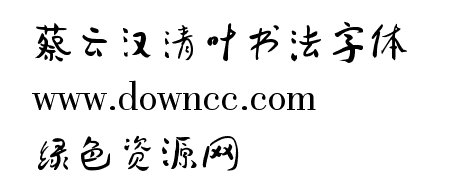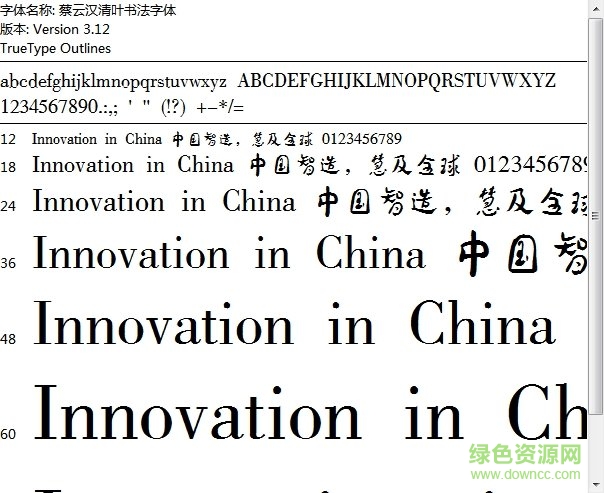
蔡云漢清葉書法字體是一款與蔡云漢清悠書法字體比較相似的蔡云漢字體,英文造型沿用了常見的字體模板,中文文字更加端方嚴謹,書寫流暢筆畫清晰,歡迎來綠色資源網下載體驗!
蔡云漢清葉書法字體整體效果出眾,字形大氣,字庫完整,可用于包裝印刷、簽名設計、電影字幕、圖形設計等領域,是一款應用于設計方面的簡體中文漢字。
蔡云漢,本名蔡昌,號明云居士。山東菏澤人,好三教性命之學。從事書法和傳統(tǒng)文化教育工作,蒙庭訓,好翰墨。幼時學柳,少致力于顏,長則涉歷代諸法帖,后以金文氣韻入草書之中。于傳統(tǒng)書法的學習和繼承中,倡導書法文化的實際功用-------文以載道,即從書法學習和創(chuàng)作審美的過程中,使自己和他人體會到中華文化的淑世價值,于是修身養(yǎng)心,歸于中正平和。